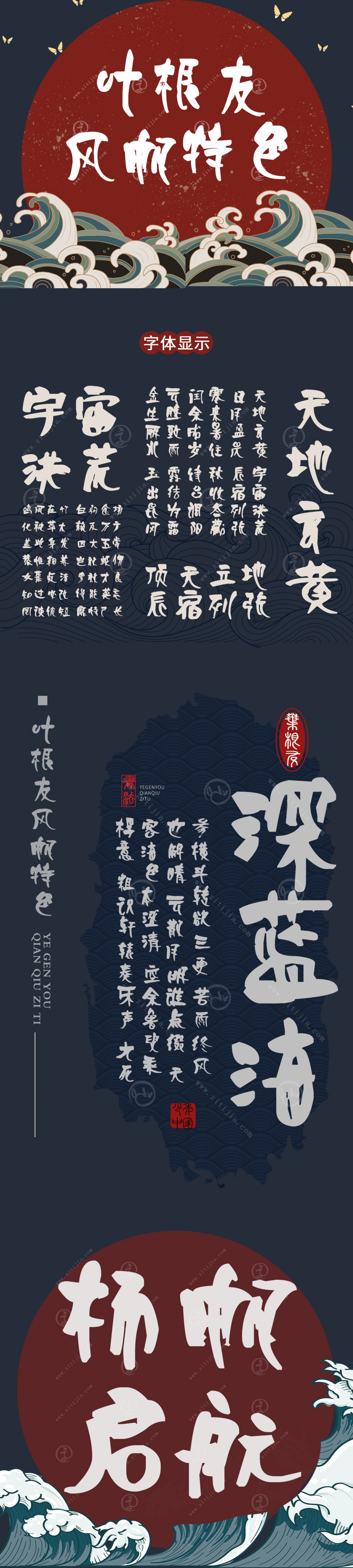
葉根友風(fēng)帆特色
字體作者:葉根友
創(chuàng)作年代:2008年
字體字?jǐn)?shù):6763個(gè)中文漢字以及其他英文字母和阿拉伯?dāng)?shù)字
字體介紹
葉根友風(fēng)帆特色字體是一款以帆船的造型來(lái)設(shè)計(jì),風(fēng)格獨(dú)特,寓意深遠(yuǎn),整個(gè)字體向右傾斜,字體富有更新的書(shū)法創(chuàng)新思維,不落俗套。在筆畫(huà)對(duì)稱(chēng)學(xué)中屬于是一種不走尋常思維的漢字字體創(chuàng)意,融合了中國(guó)書(shū)法黃金分割法則的側(cè)重理念。